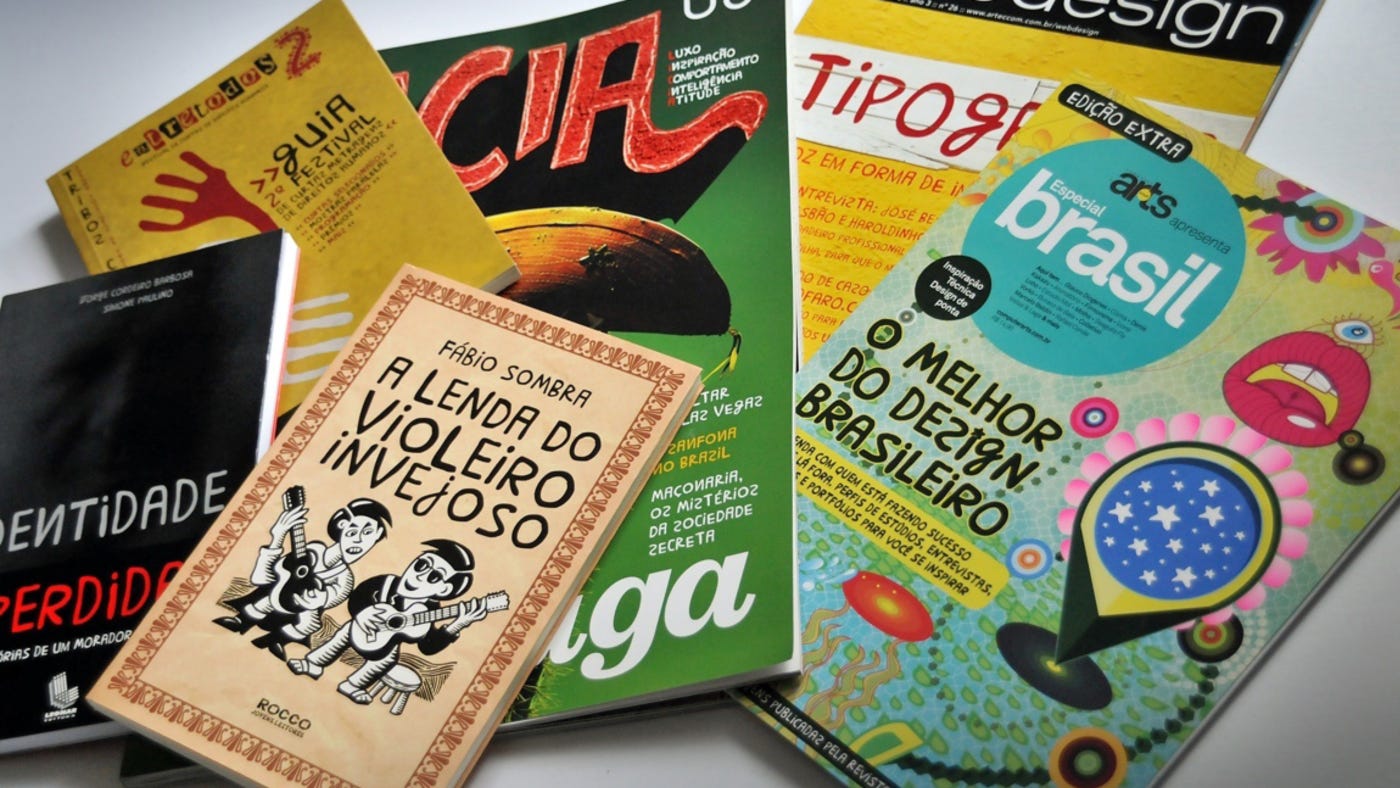
Vamos falar de fontes #4 – Brasilêro e 1 Rial
Letras vernaculares brasileiras na tipografia digital
Falar do cenário do letreiramento vernacular brasileiro é algo que facilmente ocuparia várias edições do Tipo Aquilo. A forma com que os abridores de letras manifestam-se em lugares diferentes do Brasil ainda é pouco estudada, perto do que ela pode oferecer em soluções criativas e inspiração para calígrafos, type designers e ilustradores de letras. A variedade de trabalhos que apoiam-se em pesquisas como as dos pintores de letras de Pernambuco e do Pará, desde suas publicações, é um exemplo do quanto a letra popular brasileira merece ser estudada.
Por isso, essa edição do Vamos falar de fontes foge de seu estilo tradicional para tratar de dois frutos tipográficos do olhar cuidadoso ao letreiramento popular brasileiro, e prestar reverencia tanto aos designers citados e suas fontes, quanto a todos que aventuram-se com uma necessidade na cabeça e um pincel na mão para pintar letras.
Brasilêro, de Chrystian Cruz
Esse interesse pelas letras vernaculares como referência tipográfica não é um fenômeno recente. Durante a onda experimentalista de tipografia digital no Brasil na década de 1990 e o começo dos anos 2000, vários designers aventuraram-se em criar fontes digitais baseados em referências populares. Algumas, mais específicas, como o Profeta Gentileza ou o Bispo do Rosário; outras, mais abrangentes, agregando desenhos espalhados em pontos diferentes.
Essa abordagem abrangente foi tomada pelo designer e professor Crystian Cruz para a criação da Brasilêro (sim, com ê mesmo), que é uma das fontes brasileiras mais usadas tanto no Brasil quanto mundo afora. É improvável que voce não tenha visto ela sendo usada em alguma peça publicitária, capa de livro ou CD, revista ou banner digital. Desenhada em 1999 e lançada em 2003, a Brasilêro inspira-se em letreiros populares discretamente perdidos pela paisagem urbana ou espalhados em beira de estrada, feitos sem o rigor técnico de abridores ou tipógrafos com mais experiência.
Só que é exatamente esse abraço às formas tortas e sem eixo uniforme, casamentos improváveis entre formas cursivas e romanas, e desenhos pouco ortodoxos (como o “A” quadrado) e até “errados” de letras (como o “N” e o “S” invertidos), que torna a Brasilêro tão distinta, famosa e bem-sucedida. Cada letra facilmente faz você pensar em “eu já vi uma placa com um ‘J’ desses lá perto de casa” ou algo assim.
Mas não é apenas de imperfeição que a Brasilêro é feita. Ela não se limita a uma colagem de letras espalhadas em placas diversas, oferecendo um contraste uniforme entre as formas das letras e uma leve aleatoriedade no alinhamento das letras com a linha de base, dando um caráter manual a textos compostos com a fonte. Também há uma certa aleatoriedade no contraste das letras, mimetizando a pincelada pouco hábil durante a abertura das letras. A fartura de caracteres com sinais diacríticos permite a ela ser usada mundo afora, em aplicações onde a manualidade da Brasilêro reforça valores lúdicos ou naïf.
1 Rial, de Fátima Finizola
A efervescência da produção tipográfica digital no Brasil também teve como fruto a 1 Rial, da designer e professora Fátima Finizola. Assim como a Brasilêro, ela toma o letreiramento vernacular como referência, trazendo letras maiúsculas advindas de placas de pequenos comércios de Recife, capital de Pernambuco. Lançada em 2006, a 1 Rial (sim, com i mesmo) traz um set de caracteres maiúsculos com diacríticos para a língua portuguesa, favorecendo seu uso em várias aplicações. Das mais famosas, a arte do álbum “Brasil Afora”, dos Paralamas do Sucesso.
A 1 Rial apresenta caracteres que mimetizam letras abertas de forma rústica, com pincel retangular em traços com pouca precisão. Nota-se também uma simplificação do desenho de algumas letras, como o “A”, o “O” e o “U” que utilizam desenhos retangulares, que o abridor de letras consegue replicar e harmonizar com outras letras mais facilmente. Dessa forma, a fonte proporciona uma unidade com outras letras que naturalmente lançam mão de ângulos retos e traços retos proeminentes.
Formas redondas aparecem na 1 Rial em letras como “C”, “G”, “J”, “Q” e “S”, onde é possível ver uma simplificação do traço redondo, que naturalmente exige maior destreza do pintor de letras. É possível notar também uma leve inclinação das letras — mais acentuada nas letras “M” e “N”. Essa pequena inclinação não é aleatória; ela cria um efeito de “itálico” nas letras que afasta elas de uma cultura mecanizada. Por mais retos que sejam os traços das letras, elas ainda parecem criadas por uma pessoa.
Embora a 1 Rial seja um belo trabalho de design tipográfico que presta reverência ao letreiramento popular, ela representa um recorte de um estilo específico de letras manuais. A pesquisa acadêmica que deu origem ao livro “Abridores de Letras de Pernambuco” tem importância fundamental para mostrar a riqueza da diversidade das letras vernaculares do estado, e expôr essa riqueza para o Brasil.